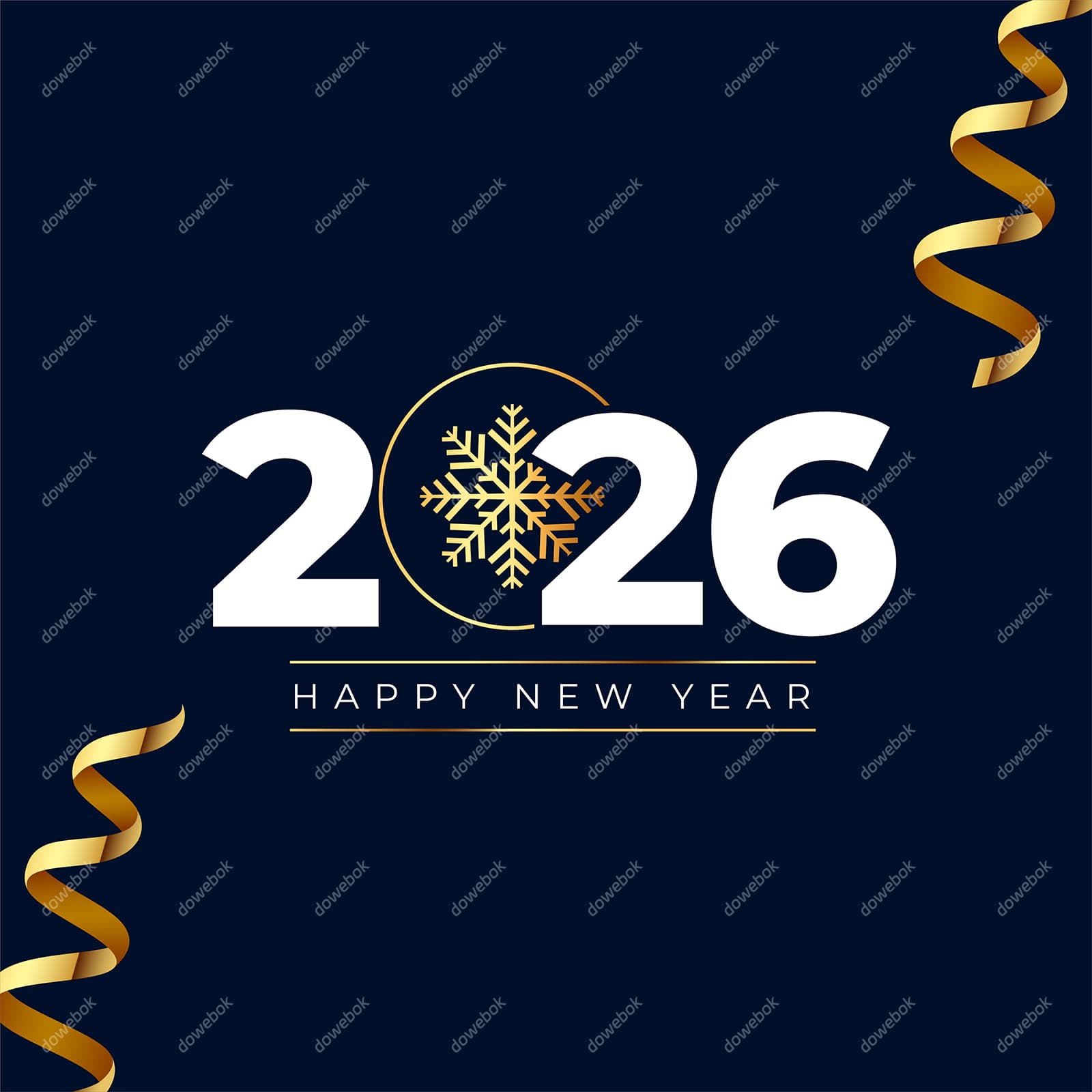
这是一款金色丝带和数字设计的 2026 新年快乐矢量素材,深幽藏蓝背景点缀金色螺旋丝带,添了节日动感。“2026” 以醒目白字呈现,数字 “0” 处嵌着金雪花纹的圆饰,呼应冬日氛围,下方 “Happy New Year” 字样以金框点缀。整体以蓝金白配色融合雪花与丝带元素,既显跨年的简约轻奢感,又用装饰细节烘托出温馨的节日氛围,沉稳中透着活泼。